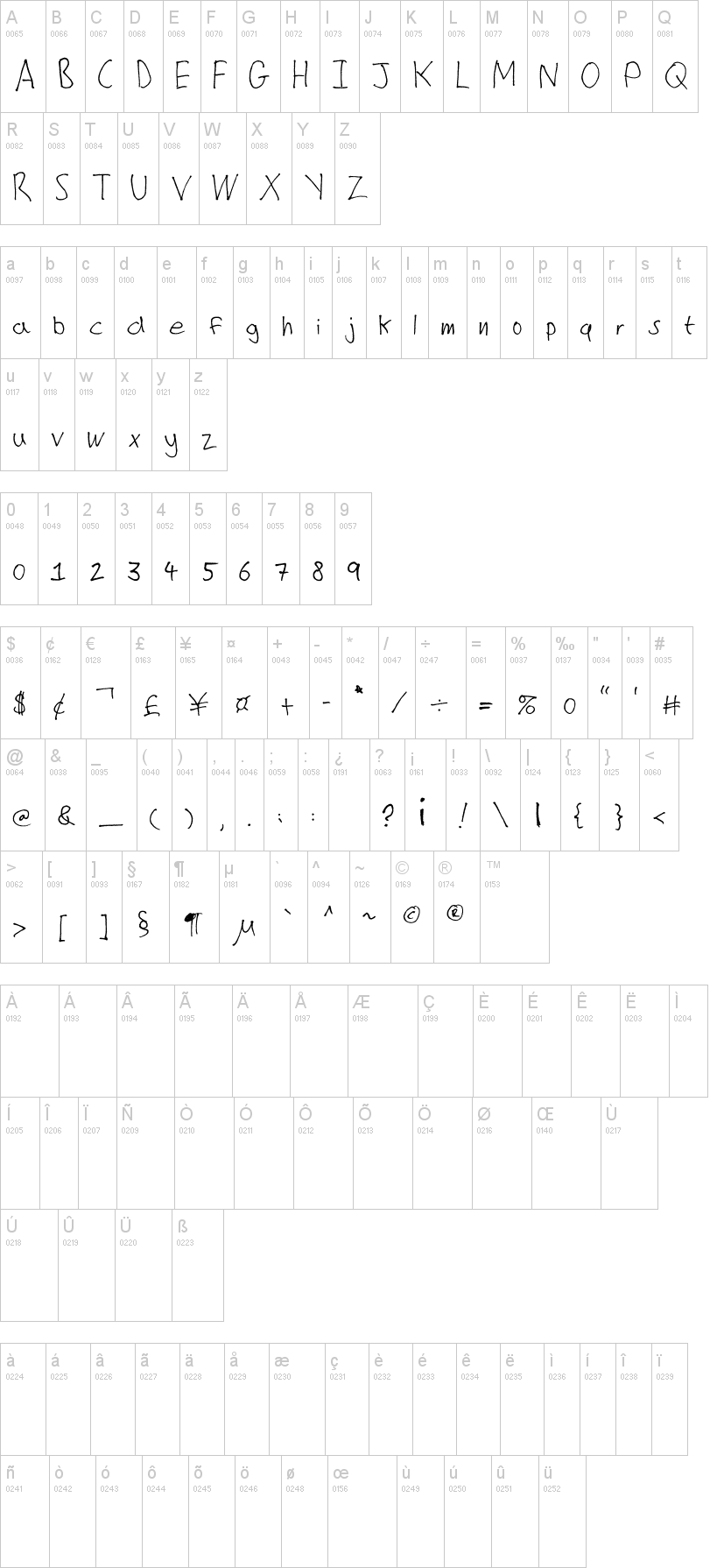
Christopher's Scribble
Christopher's Scribble 是一款个性化的手写字体,它的特点是细节丰富、个性十足,适用于各种设计场景。它的字体笔画粗细不一,每个字的笔画都有自己的特点,像是在真实的手写状态下一样,令人印象深刻。Christopher's Scribble 字体可以用于各种类型的设计,如海报、logo、书籍封面等,能够带给用户更多的设计创意。
Christopher's Scribble是一款非常不错的手写艺术字体,具有很好的视觉感,适合于文化类的宣传设计、商业类品牌的广告和产品包装设计以及个性化文字排版等较多场景。
Christopher's Scribble字符映射图